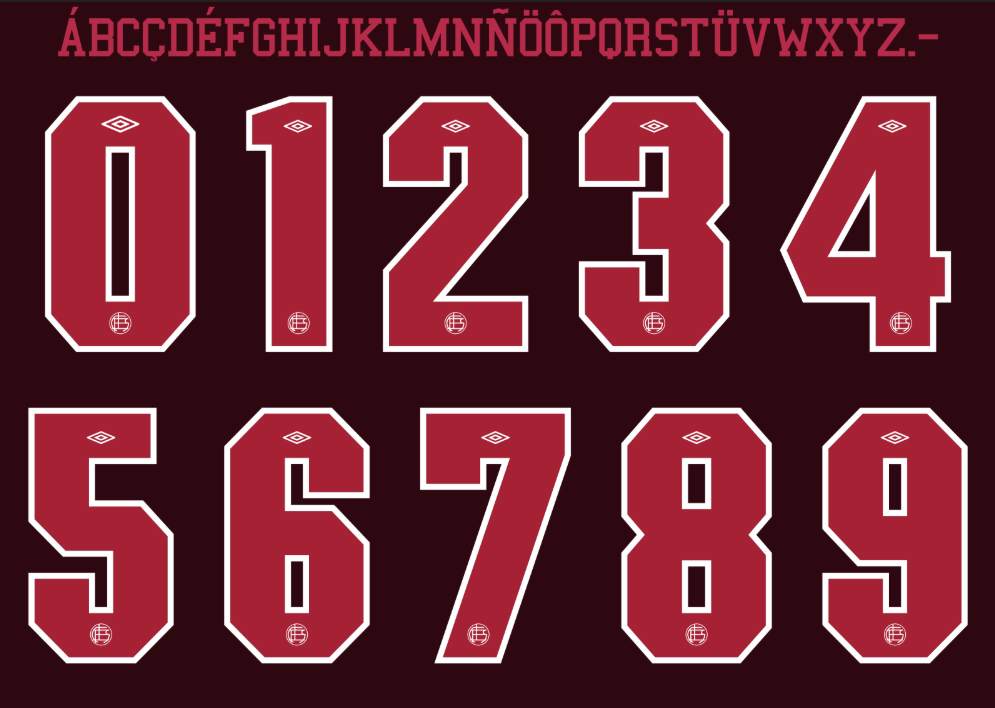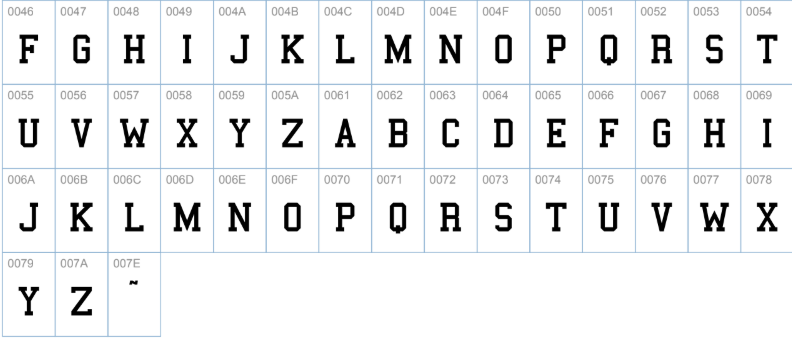
A temporada de 2026 traz novidades para o orgulho do sul de Buenos Aires. O Club Atlético Lanús, conhecido mundialmente como “El Granate”, continua sua parceria de sucesso com a fornecedora italiana umbro, apresentando uniformes que misturam a tradição da cor grená com cortes e tecnologias modernas.
A identidade visual de um time vai muito além das cores; ela passa pela tipografia estampada nas costas dos jogadores. A fonte utilizada nesta temporada reflete a solidez e a garra do time argentino. Seja para recriar o uniforme em games, desenvolver projetos de design ou estampar mockups, ter o arquivo correto da fonte é essencial para garantir o realismo da sua arte.
Neste artigo, disponibilizamos para download a fonte Lanus 2026, uma recriação digital detalhada e inspirada na tipografia oficial utilizada pelos craques do Lanús nas competições nacionais e continentais deste ano.
Estilo visual da tipografia
A tipografia desenvolvida para o uniforme do Lanús em 2026 segue uma estética limpa e funcional, característica marcante dos trabalhos recentes da umbro.
- Design: A fonte aposta em linhas geométricas com espessura média a grossa, garantindo excelente leitura tanto à distância (no estádio) quanto nas transmissões televisivas.
- Personalidade: Os números possuem contornos sólidos e ligeiramente arredondados em vértices específicos, transmitindo uma sensação de modernidade sem perder a robustez clássica do futebol argentino. É uma fonte que impõe respeito e organização visual.
- Aplicação: Nos uniformes oficiais, a fonte é geralmente aplicada em branco sobre o fundo grená (camisa titular) ou em grená sobre o fundo branco (camisa reserva), mantendo o contraste alto.